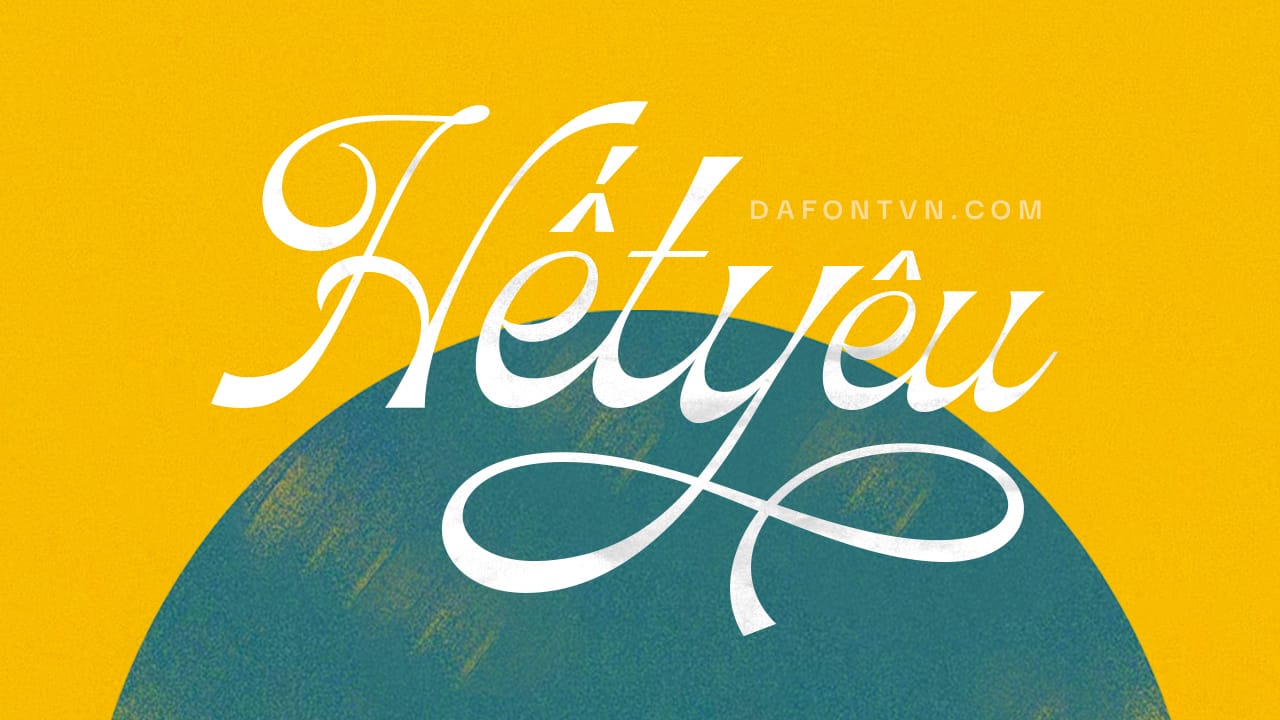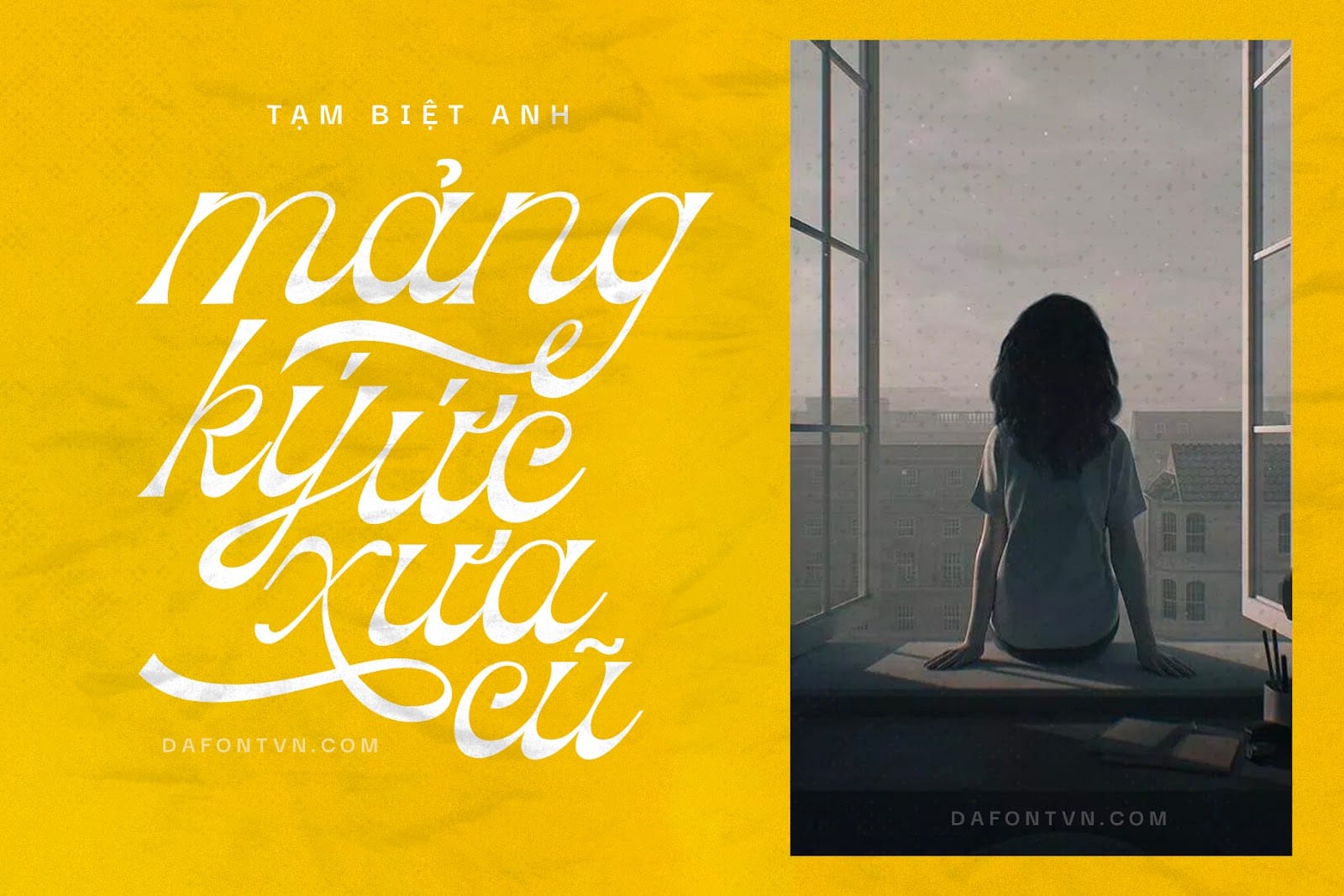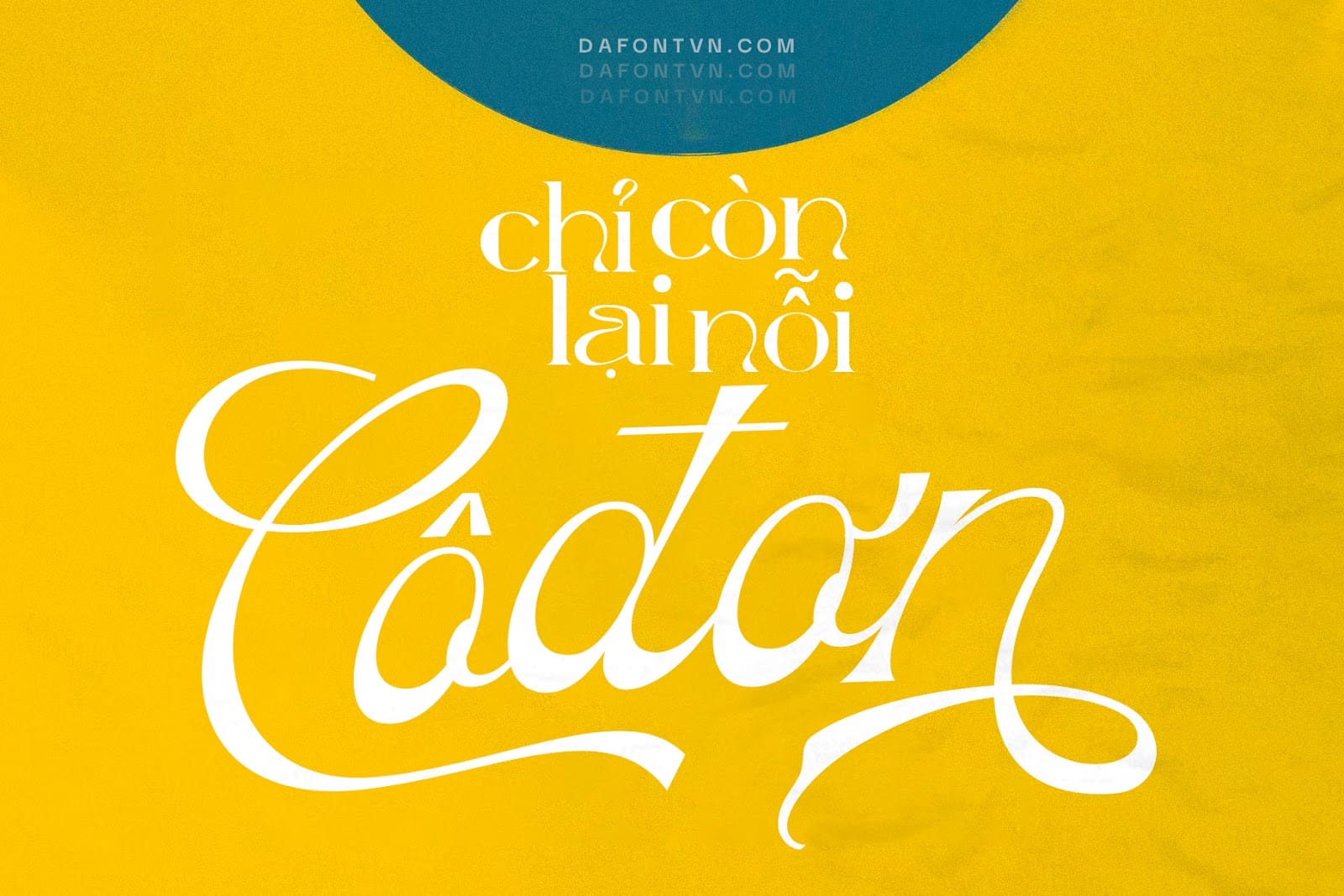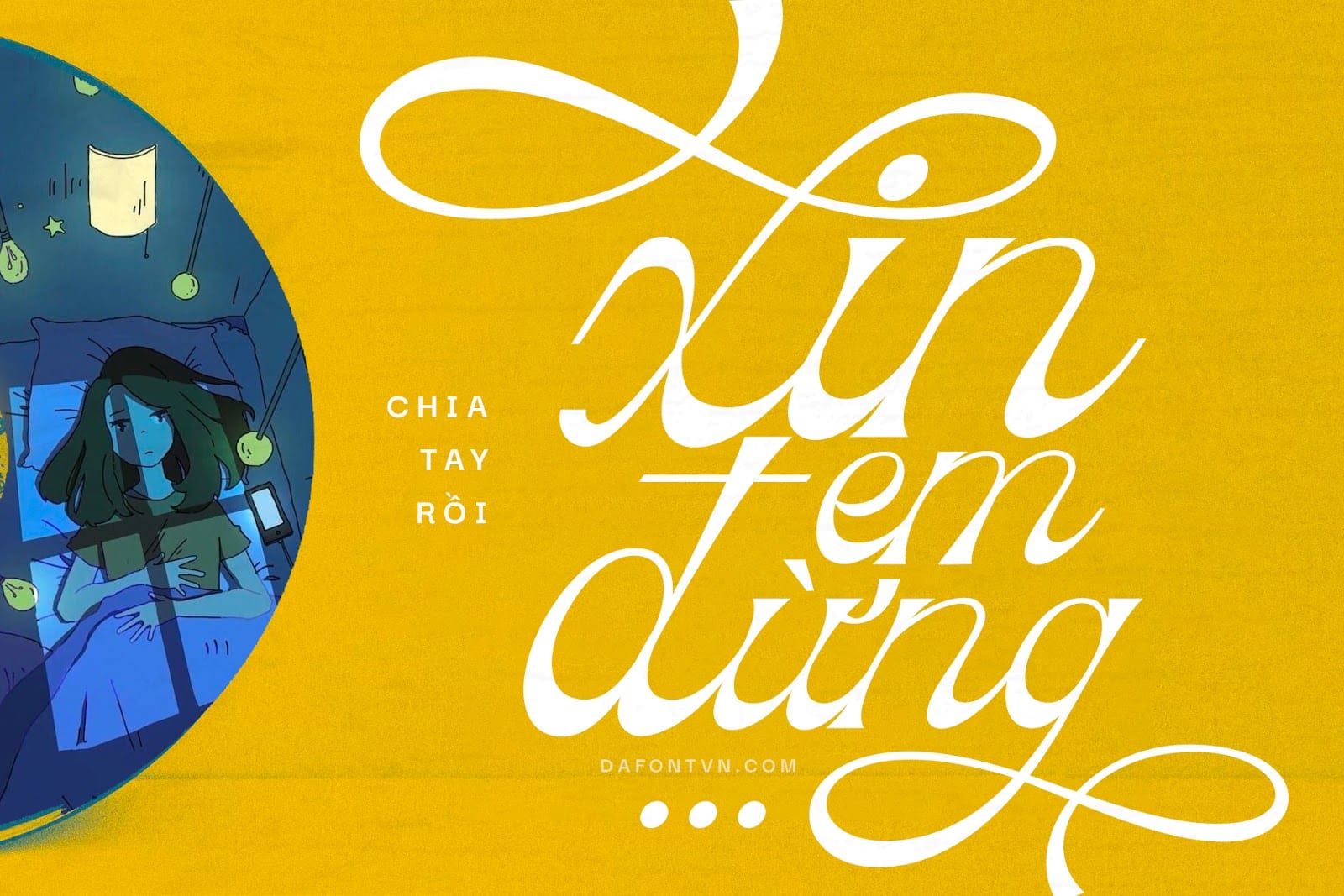
Font Hulahoy Việt hóa – Font viết tay cực đẹp
Font Hulahoy Typeface việt hóa là một kiểu font chữ viết tay cực kỳ ấn tượng được lấy cảm hứng từ phong cách thiết kế của những năm 70. Phông chữ mang một điểm nhấn ấn tượng mang hơi hướng cổ điển và hiện đại mang giá trị thẩm mỹ độc đáo.
Font Hulahoy có thể dễ dàng kết hợp với nhiều font chữ khác để tạo ra những thiết kế độc đáo. Font chữ khá phù hợp cho các thiết kế như tiêu đề, bìa sách, tạp chí, typography, quotes, thiệp mời… Để font hiển thị tốt bạn nên sử dụng font chữ ở kích thước lớn.
Ngoài ra font Hulaboy việt hóa bao gồm hơn 600 glyph độc đáo cho cả chữ hoa và chữ thường để bạn có thể dễ dàng áp dụng, thay thế các ký tự mặc định của font để tạo ra những thiết kế đẹp mắt hơn.